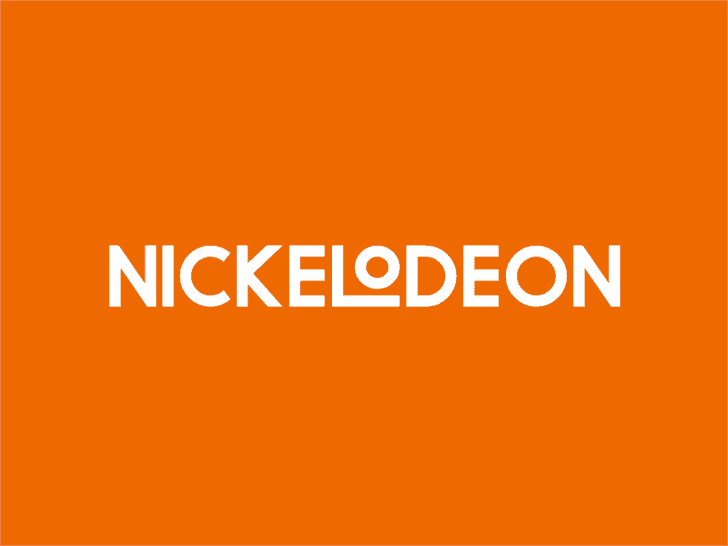
A Nickodean Playoffs font é uma escolha perfeita para designers que buscam um estilo moderno e versátil, inspirado na identidade visual dos clássicos jogos de futebol do Nickelodeon. Embora possa ser chamada alegremente de “logo” da Nick desapropriado, essa font foi verdadeiramente inspirada em um projeto de Behance que trouxe uma beleza única e inovadora para o design. Se você está procurando por uma fonte de exibição com personalidade, sem dúvida essa será uma ótima opção. Sua simplicidade arrojada permite que seja usada tanto nas capas de revistas quanto em banners digitais, garantindo que sua identidade visual saia do papel e entre na esfera digital. Com seu designer residente Hamilton, Nickodean Playoffs oferece a oportunidade de criar um design único e moderno, sem deixar para trás o brilho inconfundível da Nick.